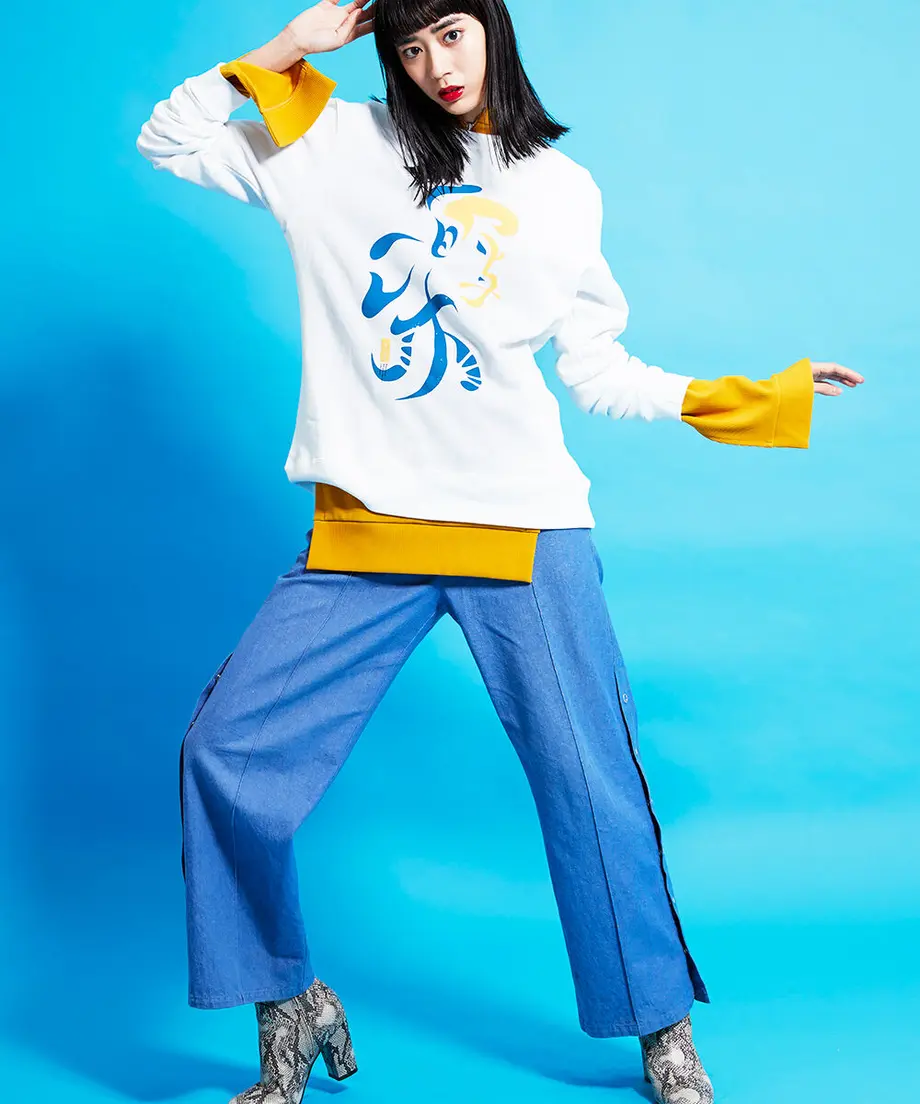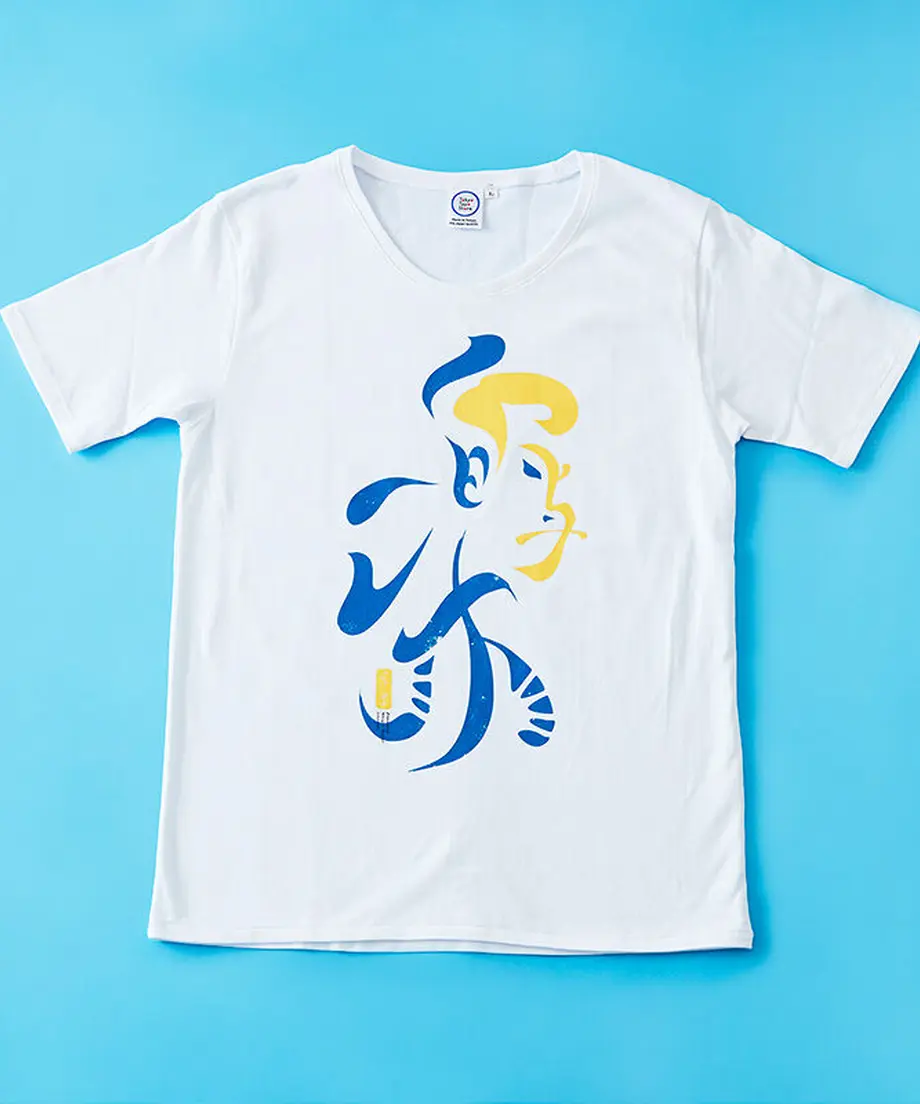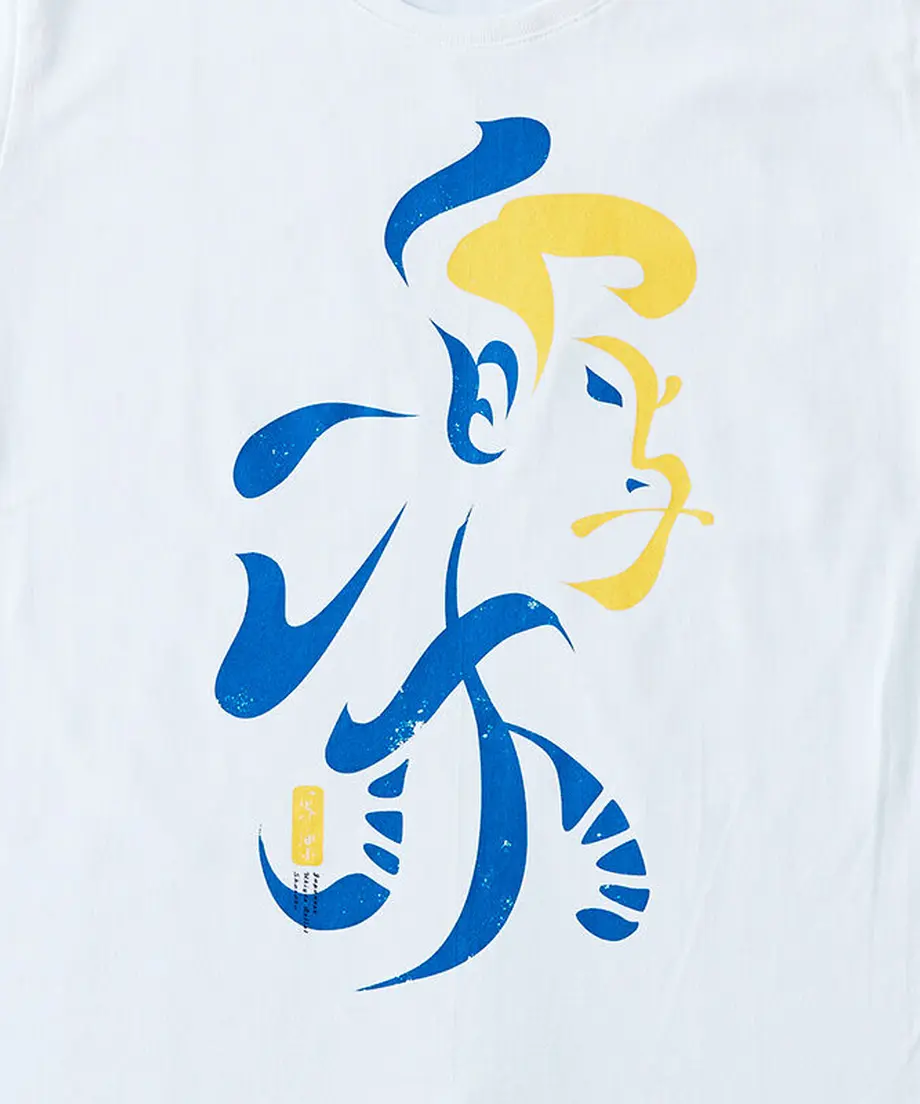
日本を代表する浮世絵師「写楽」。その写楽の文字で写楽の代表的な作品「大谷鬼次の奴江戸兵衛」をカラフルにデザインしました。
Sharaku, an ukiyo-e artist and a representative of art in Japan. Sharaku’s writings are used to provide a colorful design to his exemplary piece Ōtanioniji no yakkoedobei.